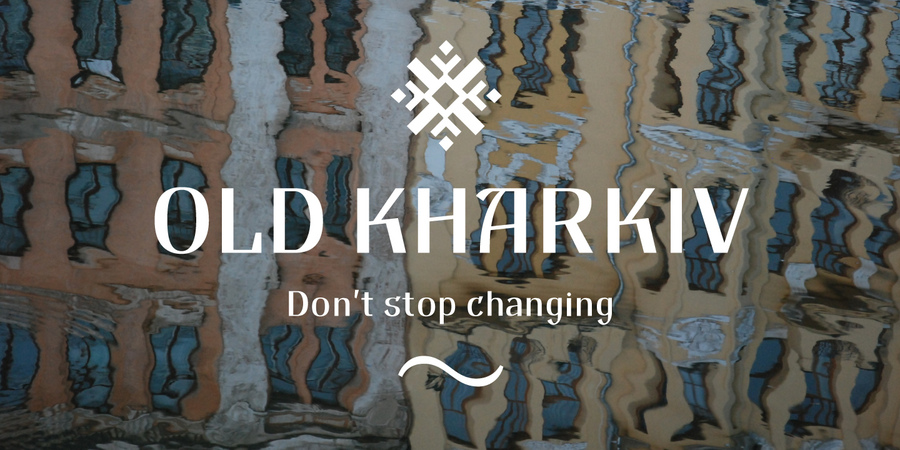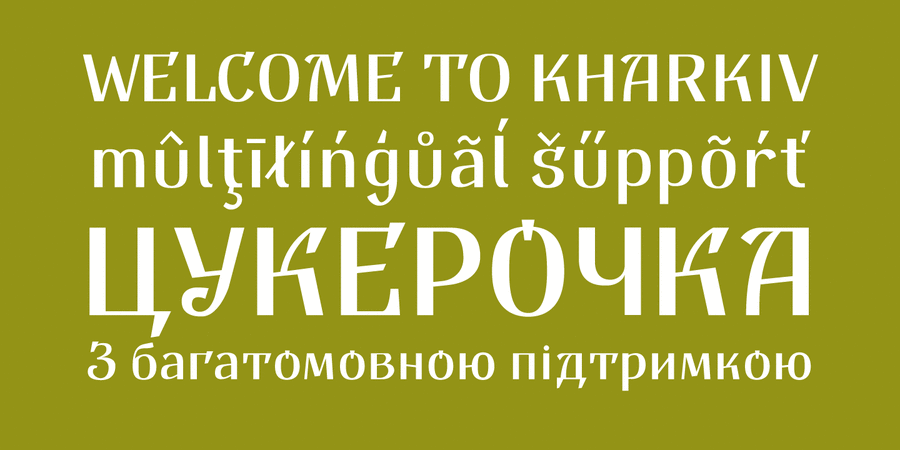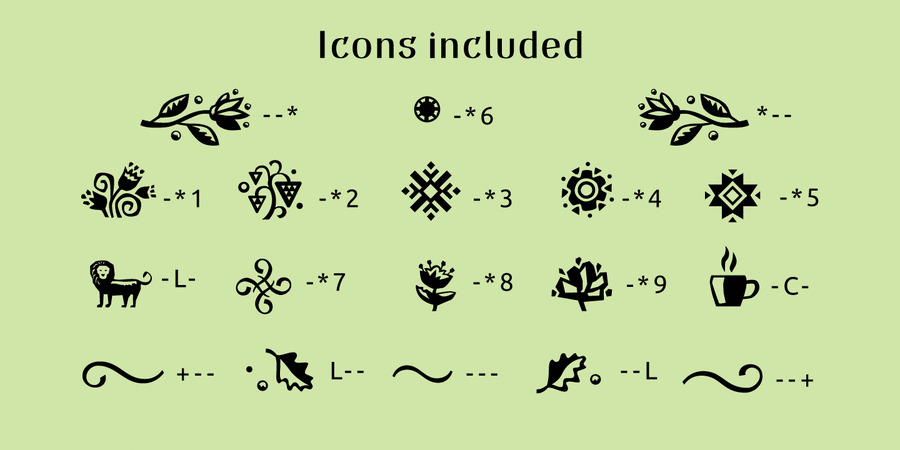
Шрифтова пара з Kyiv Extra Bold (1 з 31)Опис шрифта Old KharkivПоштовхом до початку роботи над шрифтом «Старий Харків» стала фотографія першої половини 20 століття з вивіскою на споруді теперішнього Харківського національного університету мистецтв імені Івана Котляревського. В процесі роботи шрифт набув унікальних рис, яких не було на оригінальній вивісці, наприклад, краплі у великих літерах були замінені на зрізані різкі зарубки. У цьому шрифті подані літери усіх основних європейських мов, є набір основних спеціальних символів. Деякі великі літери (там де це дозволила їх форма) мають подовжені декоративні елементи (розчерки) аби використати їх у якості буквиці. Для деяких українських літер (Щ, Ц, Л, З, Ж) створені стилістичні альтернативи. Також у вигляді бонусу шрифт містить до десятка графічних елементів, які можна використати в тексті. Шрифт розроблено Богданом Гдалем у 2016-2017 році.
Особливості сімейства шрифтів Old KharkivХіт десятиліття:
Хіт 1910-х Хіт 1920-х Old Kharkiv підтримує 83 мовиУкраїнська, Англійська, Німецька, Польська, Португальська, Іспанська, Французька, Російська, Чеська, Голландська, Італійська, Шведська, Турецька, Фінська, Білоруська, Сербська, Болгарська, Естонська, Литовська, Албанська, Африкаанс, Баскська, Бретонська, Валенсаска, Galician, Гельська (Шотландська), Данська, Індонезійська, Ірландська, Ісландська (Win), Каракалпацька, Каталонська, Норвезька, Окситанська, Ретороманська, Самі Лулі, Тсванська, Узбецька (Лат.), Фарерська, фризька, Чаморро, Естонська (Win), Південносаамська, Албанська (Win), Угорська, Верхньолужицька, Карельська, Латвійська (Mac), Литовська (Mac), Маорійські (Mac), Молдавська (Лат.), Нижньолужицька, Румунська (Win), Словацька, Словенська, Туркменська (Лат.), Хорватська (Win), Естонська (Mac), Курдська, Латишська, Маорійські, Руминська, Абазинська, Аварська, Агульська, Адигейська, Даргинську, Інгуську, Кабардино-Черкеська, Кабардинська, Карачаєво-Балкарська, Кумицька, Лакська, Лезгинська, Македонську, Мордовсько-Мокшанська, Мордовсько-Ерзянська, Ногайська, Рутульська, Табасаранська, Татська, Цахурська, Чеченська Функції сімейства шрифтів Old KharkivЗастосування гарнітури у верстці:
Асоціації з сімейством шрифтів Old KharkivОсобистість і характер гарнітури:
історичний, екологічний, добротний, стійкий, свіжий, гострий, сміливий, самобутній, характерний, оригінальний, різкий, етнічний, натуральний, традиційний, дотепний, колоритний, артистичний, художній, дерев'яний, динамічний, ностальгічний, культурний, ремісничий, виразний, красивий, крафтовий, привітний, доброзичливий, приємний, якісний, пивний, артізанальний